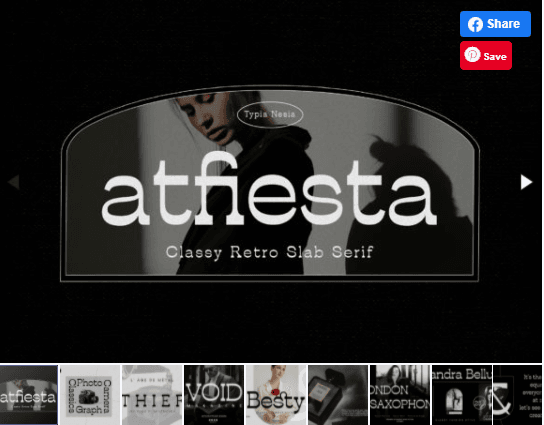
Atfiesta Font
Atfiesta - это классный, стильный шрифт с засечками в стиле ретро. Какой бы ни была тема, этот шрифт станет прекрасным дополнением к вашей библиотеке шрифтов, поскольку он может улучшить любое творение.